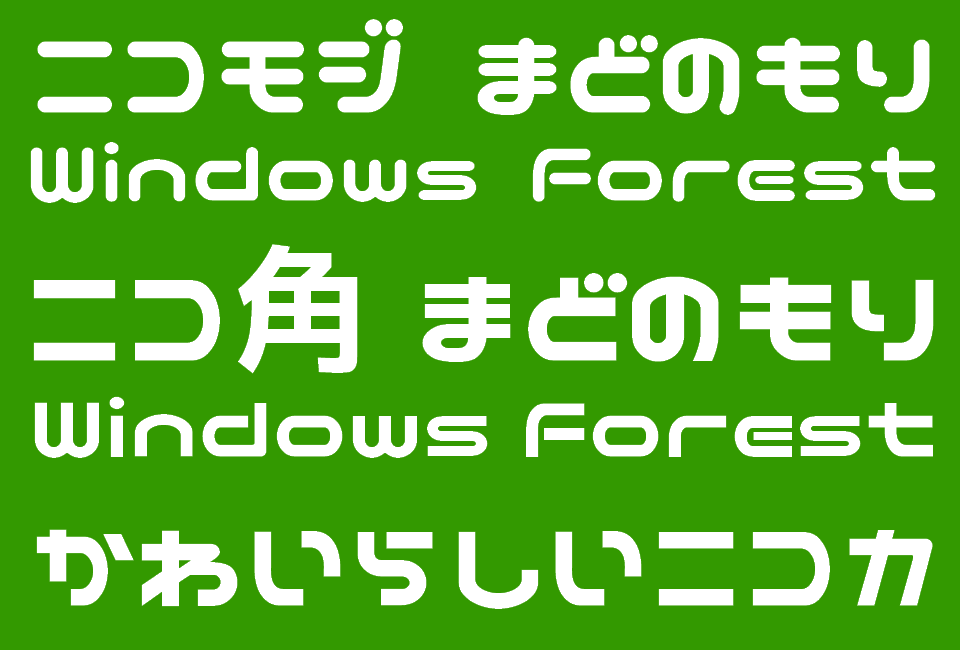
ニコニコ動画のロゴを参考にしたフォント3姉妹「ニコモジ+」「ニコ角」「ニコカ」
ユルい丸ゴシック体からキュートな角ゴシック体へと成長
「ニコモジ+」「ニコ角」「ニコカ」は、“ニコニコ動画”のロゴを参考にデザインされた仮名フォントシリーズ。いずれもひらがな、カタカナ、英数字を収録している。
「ニコモジ+」が基本の“長女”にあたり、“ニコニコ動画”のユルさを再現。ひらがなは“ニコニコ動画”のロゴに存在しないため、ほぼ独自のデザインとも言え、丸みを強調した造りがさらにユルい印象だ。また、オープンソースフォント「源ノ角ゴシック」の丸ゴシック版である「源柔ゴシック」を合成することで漢字と記号にも対応。
続く次女「ニコ角」は「ニコモジ+」の角ゴシック版であり、独特な曲線をそのままにメリハリも加えた。角ゴシック化に際し、漢字が「源柔ゴシック」から「M+ FONTS」へ置き換わっている。
最後の三女「ニコカ」は「ニコ角」の画線を短く簡略化し、キュートな雰囲気を演出。“ニコニコ動画”を起源とするものの、カタカナも含めて別物として考えてもよいだろう。